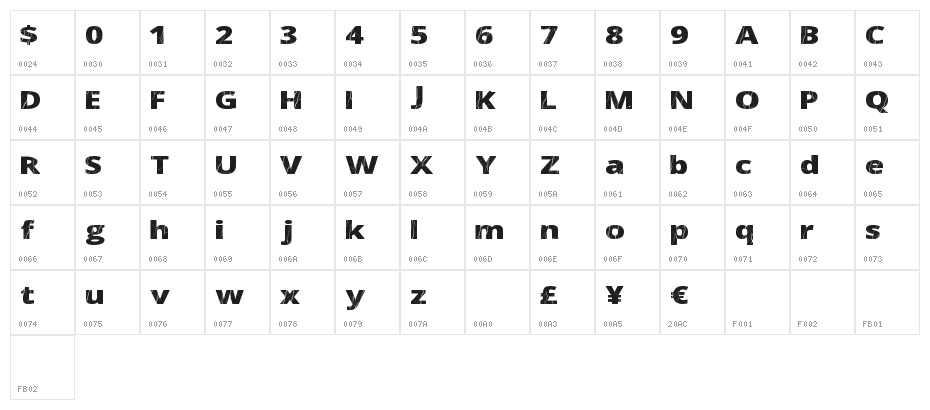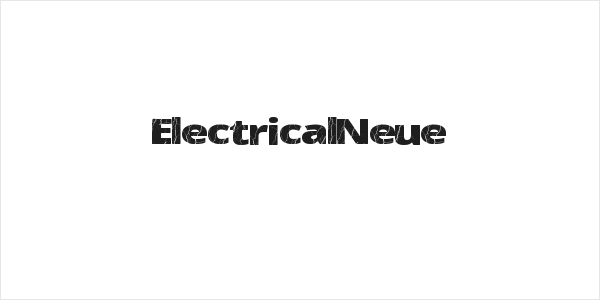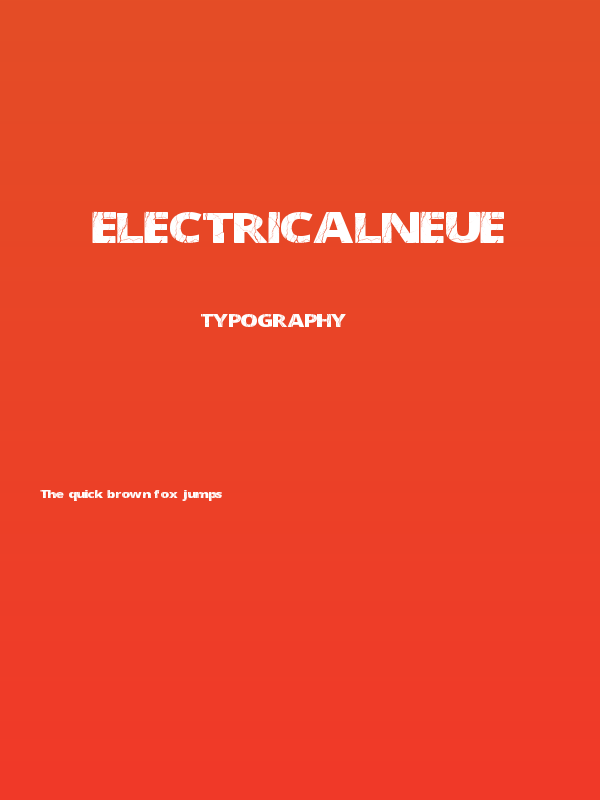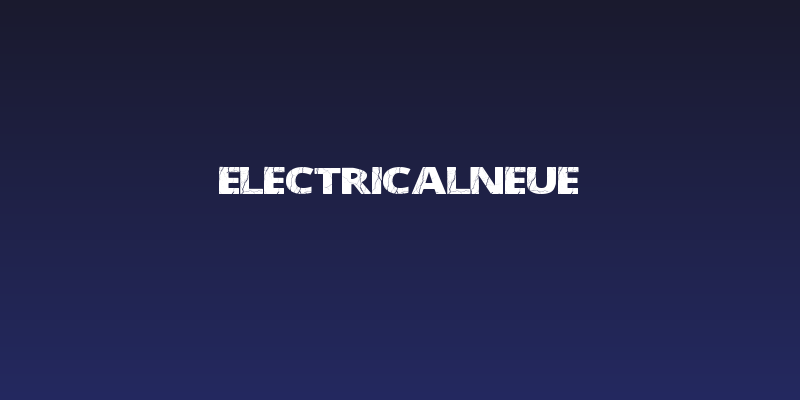
ElectricalNeue Font
| Progetti proposti | Ideal for posters, album covers, branding for edgy products, or any design needing a rugged, industrial vibe. |